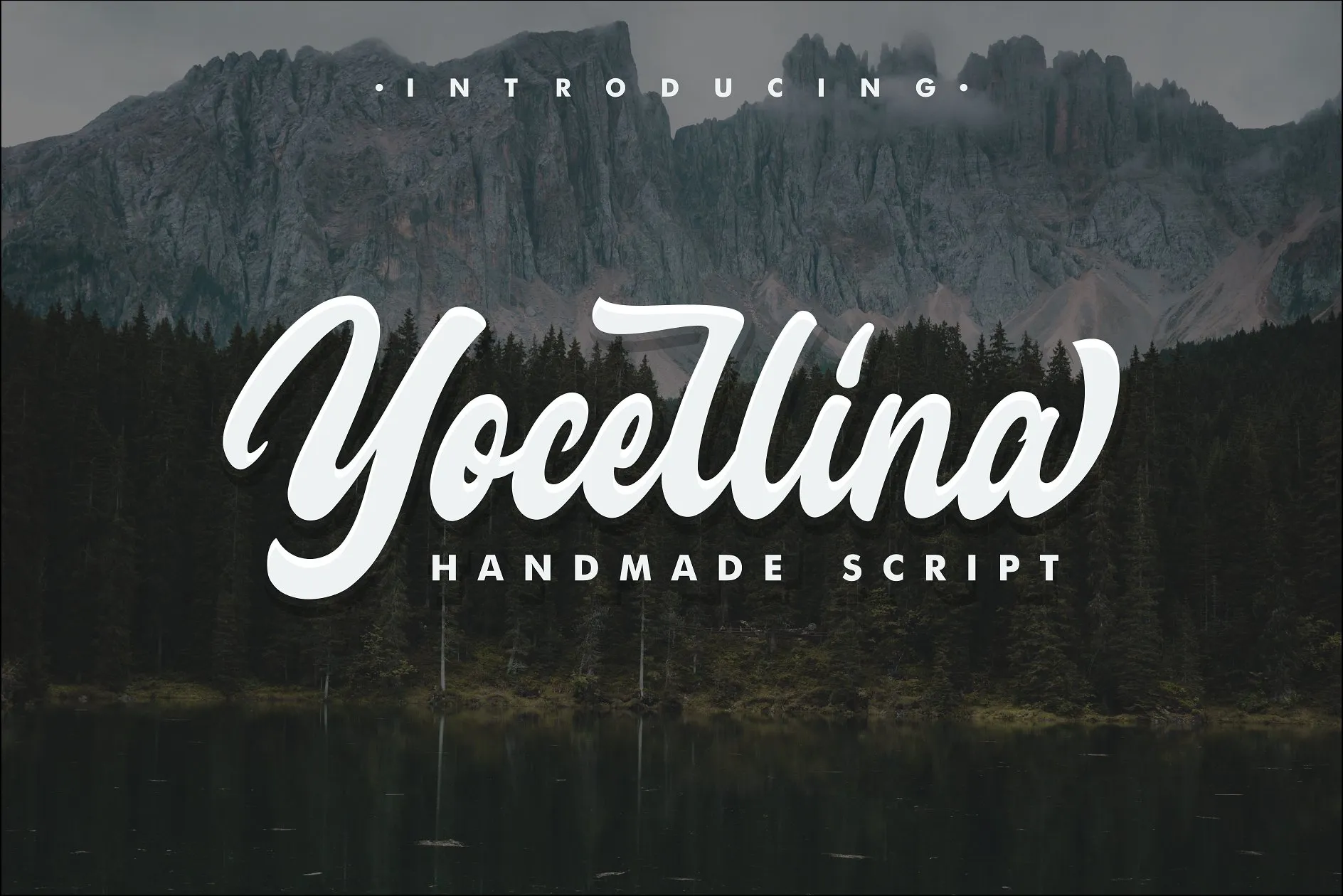
Descubra a magia única do Yocellina Script Font para suas próximas criações digitais. Especialmente desenvolvida pelo designer MouzeType, essa fonte script é perfeita para quem busca uma gradação de estilo à mão livre e autêntica. Ideal tanto para branding e logo design quanto para trabalhos como lettering, logotipo, moda, cartazes ou revistas, Yocellina oferece tudo o que precisa em um só pacote: letras maiúsculas e minúsculas, números e pontuação. O destaque é a inclusão de alternativas do tipo opentype e ligaturas comuns para cada caractere, proporcionando uma variedade infinita de customizações. É perfeito para criar identidades digitais frescas e únicas. Descubra como Yocellina pode transformar seu trabalho em um desafio mais que gratificante!